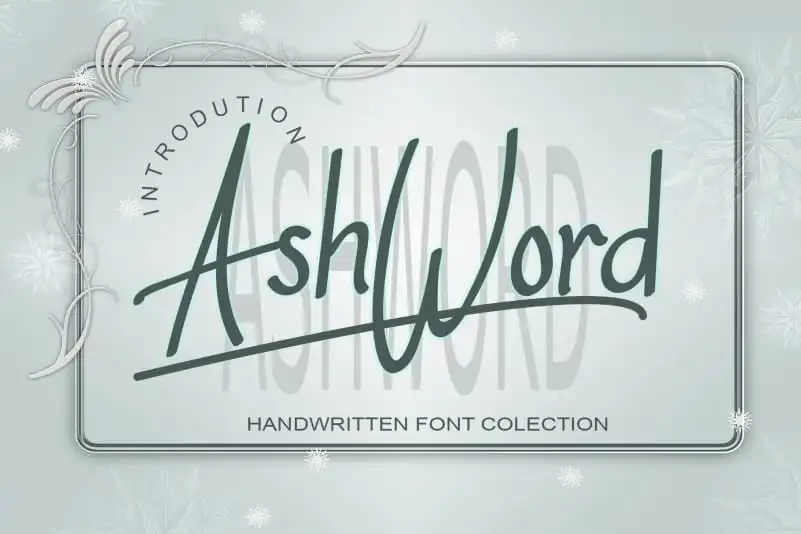
AshWord Script Font – Download Grátis
A AshWord Script Font é uma tipografia manuscrita moderna que oferece leitura fácil, forte e estilosa. Esse tipo de letra se destaca por suas curvas fluidas e perfeitas para aplicar ao branding fashion ou à design editorial. Se você adicionar essa fonte com confiança a seus projetos, certamente amará os resultados alcançados. É uma opção perfeita para quem busca um estilo único e sofisticado em suas criações visuais.